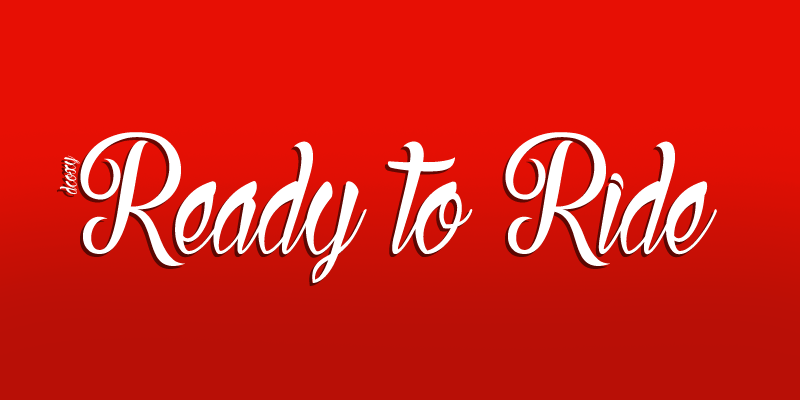
A fonte “Ready to Ride” é uma escrita ao vivo criada pelo designer Hamilton que transmite uma sensação casual mas profissional. A sua letra fluida e autêntica combina perfeitamente para qualquer projeto que deseje transmitir um estilo descontraído com um toque de sofisticação. Seja para criar material editorial, logotipos ou até mesmo mensagens promocionais, essa fonte oferece a capacidade de capturar o coração do seu público-alvo de uma maneira única e envolvente. Licenciamento: Uma licença é necessária para uso comercial ou promocional. Entre em contato conosco antes por  Esta fonte escrita ao vivo, criada pelo designer Hamilton, oferece um toque único que adicionará personalidade a qualquer projeto de design. Seja você uma empresa buscando criar identidades visuais profissionais e impactantes ou simplesmente alguém gostando do estilo casmurra da fonte para usar em seu blog pessoal, certamente há espaço para a “Ready to Ride” ser parte integral desse universo visual.